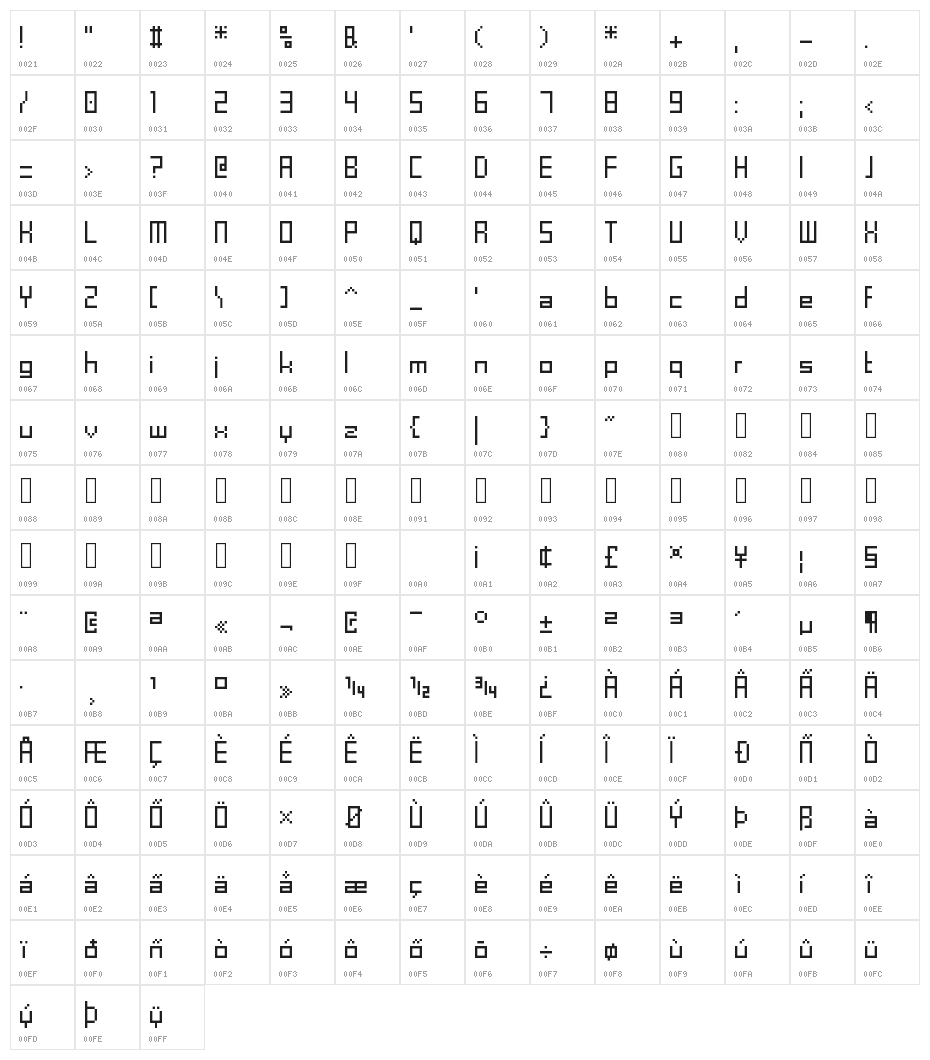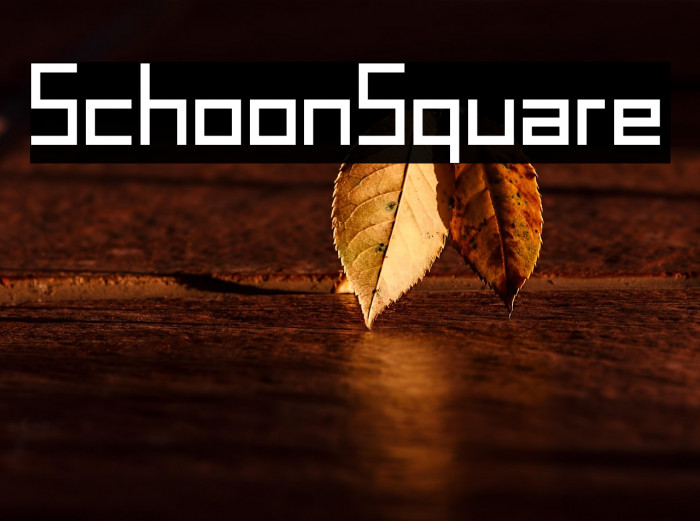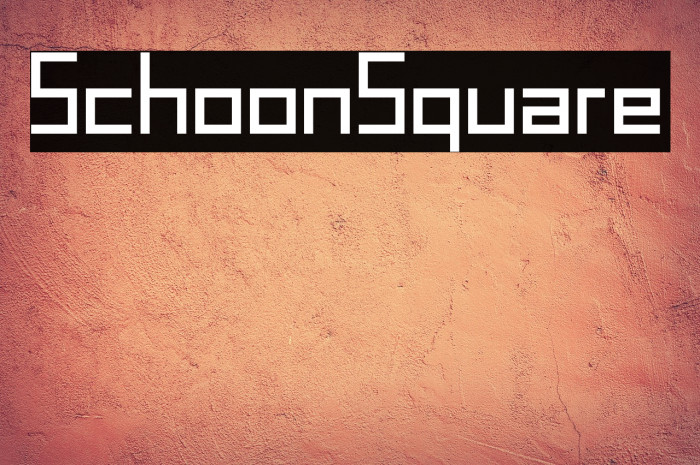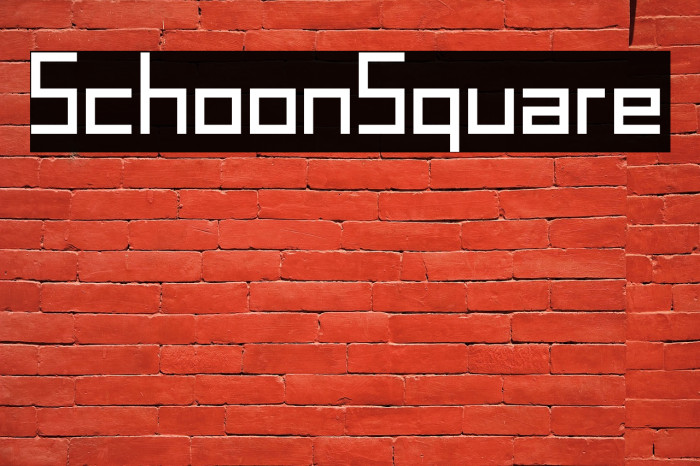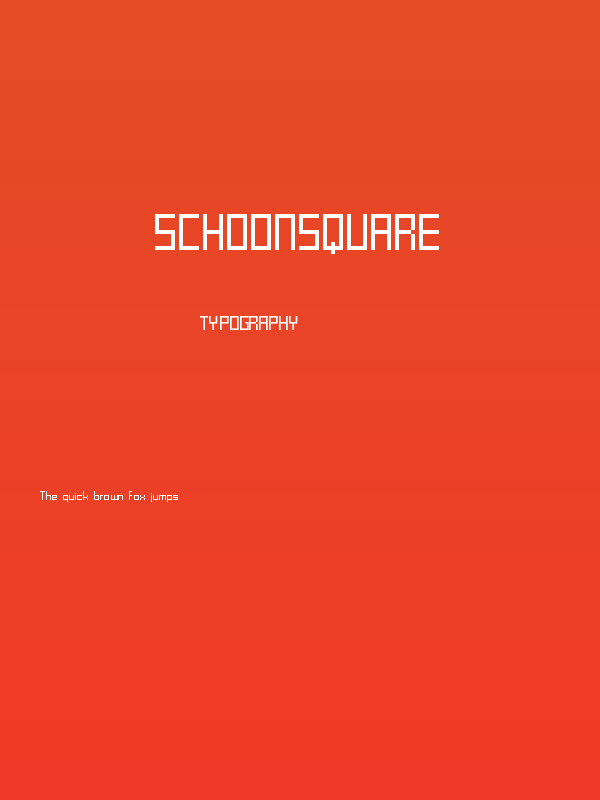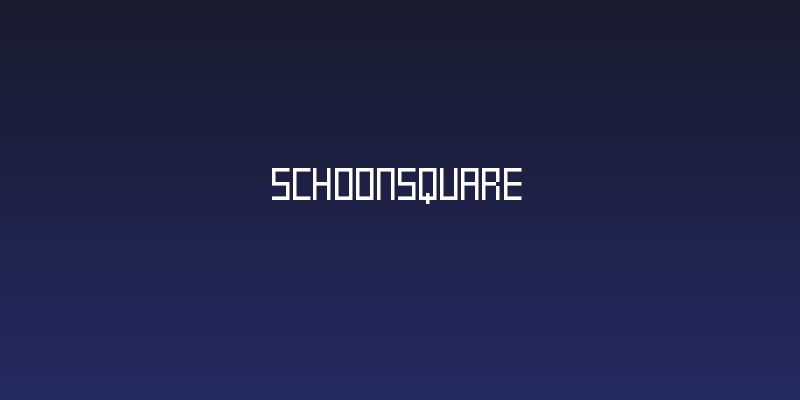
SchoonSquare Font
| Nome | SchoonSquare |
| Stile generale | Modern, Retro |
| Caso d'uso | Logos, Headlines, Digital displays |
| Progetti proposti | Ideal for digital art projects, retro-themed designs, video game graphics, and tech-related branding. |